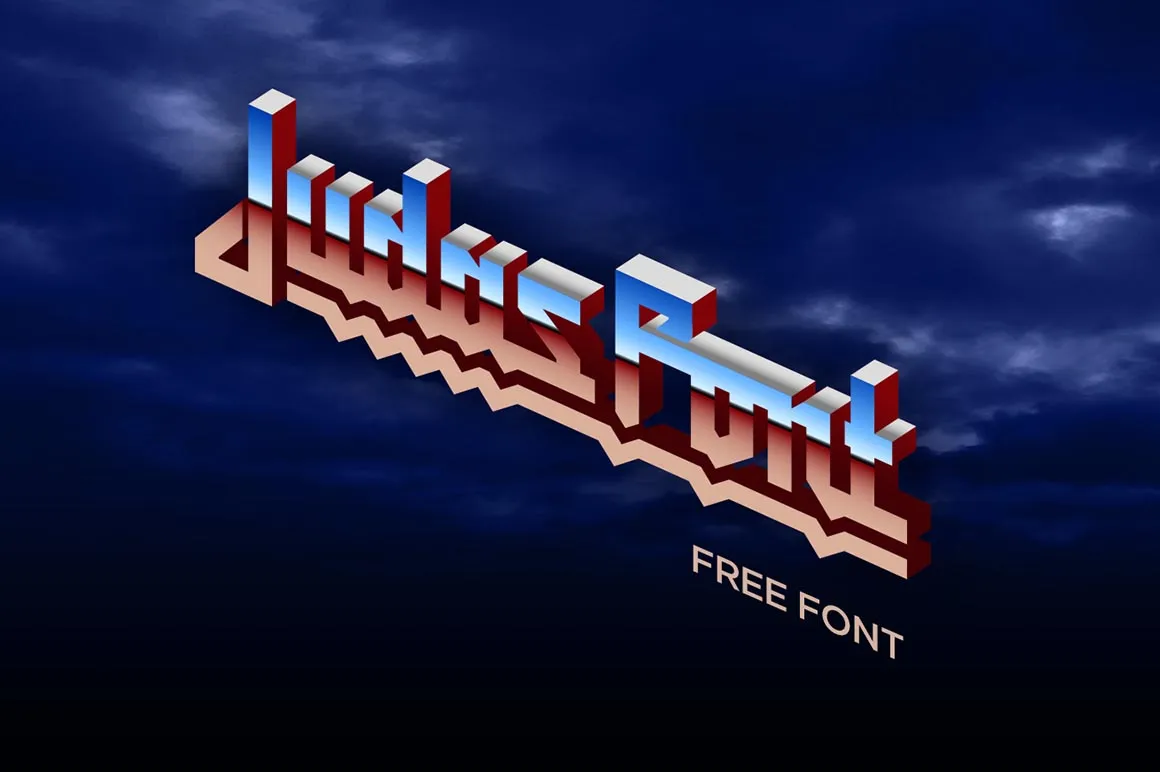
Judas Font – Fonte Grátis
Judas Font
Judas Font é uma elegante escolha para designers que buscam adicionar um toque moderno ao seu projeto visual. Este estilo Gothic foi criado por Hamilton e traz consigo linhas finas, curvas suaves e características distintivas que remetem à era futurista ou contemporânea. Com seu design minimalista e forte, Judas Font se destaca como uma opção versátil para nomes de empresas, títulos em publicações ou qualquer outro aplicativo onde um estilo elegante e inovador é desejado. Características que chamam a atenção incluem ponteiros curtos e linhas finas que criam um contraste interessante. Este font é especialmente adequado para quando você deseja criar um design com um ar distinto, combinando ao mesmo tempo sofisticação e modernidade. Com Judas Font na sua paleta de recursos, transforme suas criações num clique.